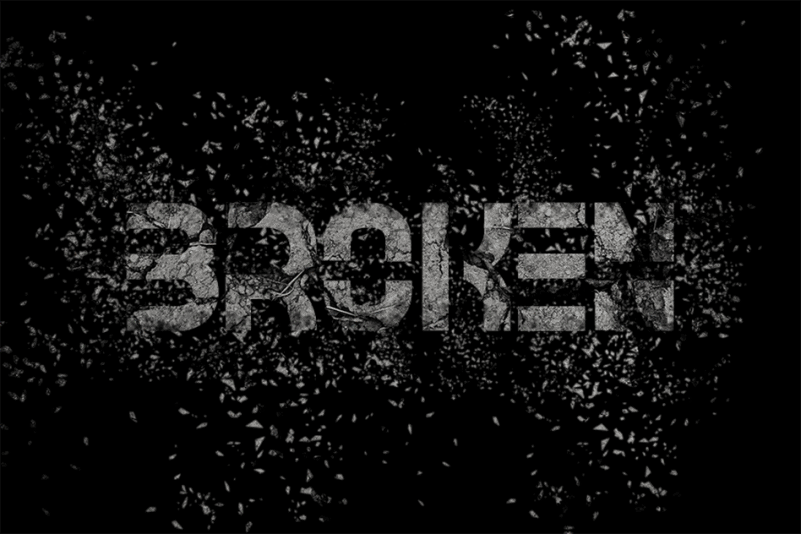
A fonte ‘Broken Display Font’ é uma escolha incrível para qualquer projeto criativo que deseja destacar-se. Desenvolvida pelo designer Erik Studio, esta fonte destaca-se por seu estilo cool e audacioso, ideal para criar designs impactantes. Seu design cuidadosamente pensado faz com que sua criação se destaque de forma notável, capaz de impulsionar as suas ideias criativas ao extremo. Com ‘Broken Display Font’, você pode transformar qualquer projeto em algo realmente especial e inusitado. Este é o ideal para designers buscando dar um toque único a seus projetos, seja ele digital ou impresso. Não hesite em experimentar este fonte audaciosa que certamente fará sua marca de forma imediata.